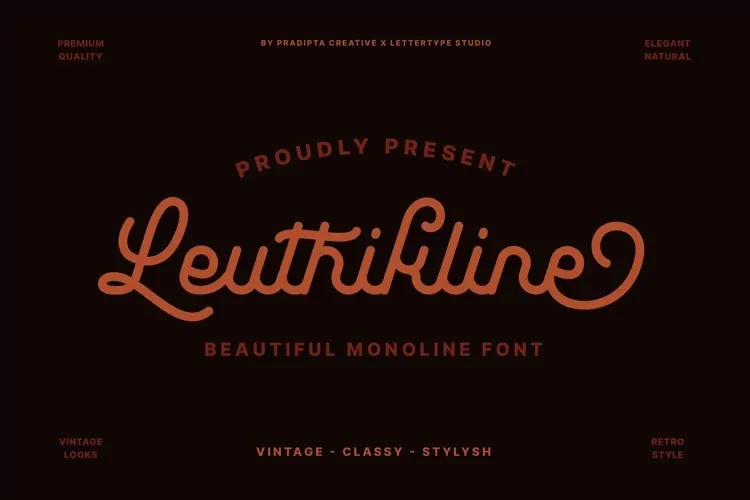
A fonte Leuthikline é uma elegante tipografia script mono-line criada pelo designer Pradipta Creative. Com traços robustos, texto ergonômico e um toque de ligaturas personalizadas, ela se destaca como perfeita para criação de logotipos, design de marcas, roupas, sinalização, cartazes, convites de casamento e muito mais. Suas linhas fortes e sua disposição moderna tornam-a uma escolha ideal para quem busca uma fonte de script clássico com um toque divertido e versátil. Ideal tanto para criações digitais quanto impressão, Leuthikline é perfeita para qualquer projeto que exija elegância e sofisticação.